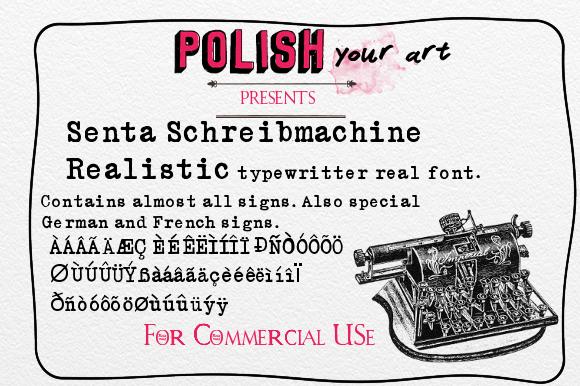
Schreibmaschinen-Schriften (sauber und dreckig)?
Fraktur-Schreibmaschinen waren aber schon eine Nazi-Marotte (eben vor 1941) — oder wie jetzt? Vor 1933 hergestellte Maschinen waren anscheinend ein ziemliches Nieschenprodukt.
Am 8. August folgte er [Reichsinnenminister Wilhelm Frick] einer Anregung des Buchhändlerischen Fraktur-Bundes und ließ für das Innenministerium anordnen, nur noch „Schreibmaschinen mit deutschen Schriftzeichen“ anzuschaffen. Es ist nicht bekannt, wie viele dieser Schreibmaschinen tatsächlich angeschafft und benutzt wurden.
Ansonsten hab ich nur noch von Schreibmaschinen mit zusätzlichen Sigrunen gelesen.
Dieser alter "faden" (schön das es noch solche deutsche wörter gibt - statt thread) birgt hübsche und böse überraschungen: die fraktur typewriter und der bormann brief). frage an den experten: welcher "normalschrift" hat bormann gemeint und wann wurde diese eingeführt und was hatten die nazis mit der verbreitung der dinschrift zu tun?
ich fand noch die thesis sans typewriter, ein wenig in der richtung der beowolfserie.
Senta Schreibmaschine.  Die habe ich mit Hilfe eine echte Schreibmaschine erstell :
Technik: Typenhebelmaschine mit Vorderaufschlag und doppelter Umschaltung Erscheinungsjahr: 1912 Hersteller: Frister & Rossmann Aktiengesellschaft, Berlin Konstrukteur: Franz Kraudzun
POLISH […]
Contains all signs you need
Gdzie są Ą, Ł i Ż?
Nikt do tej pory nie potrzebowal...sa niemieckie i francuskie. Jezeli bedzie klient na polskie to dorobie....na razie nikt nie chcial.😉